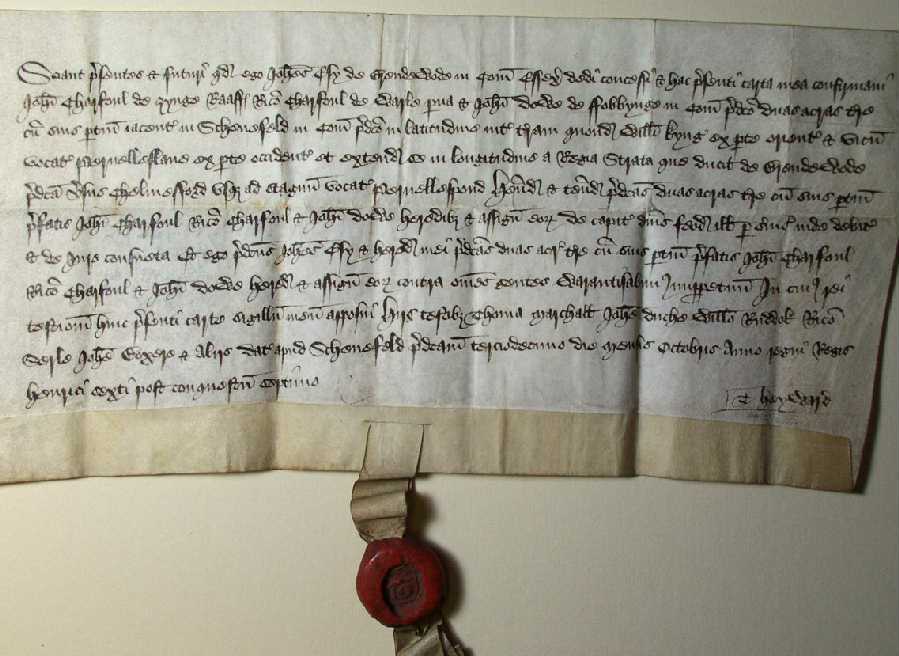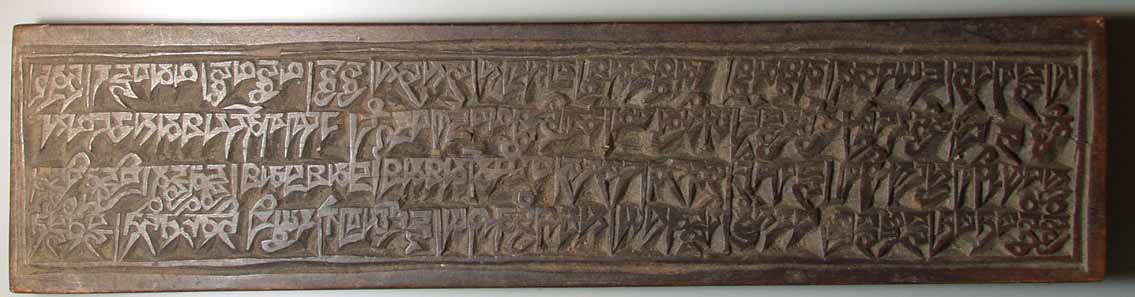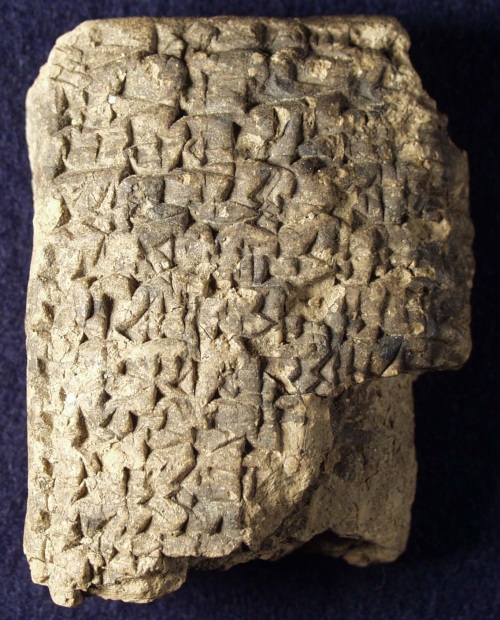
モンゴル時代(13-14世紀)の文字文化(継続)
モンゴル時代(13-14世紀)の文字文化
■各種パスパ文字資料(印鑑、貨幣、銅錘、拓本)
■モンゴル時代諸ハン国貨幣
■その他
世界の“あいうえお表”
〜児童教育用の絵入り大型文字表と文字練習帳〜
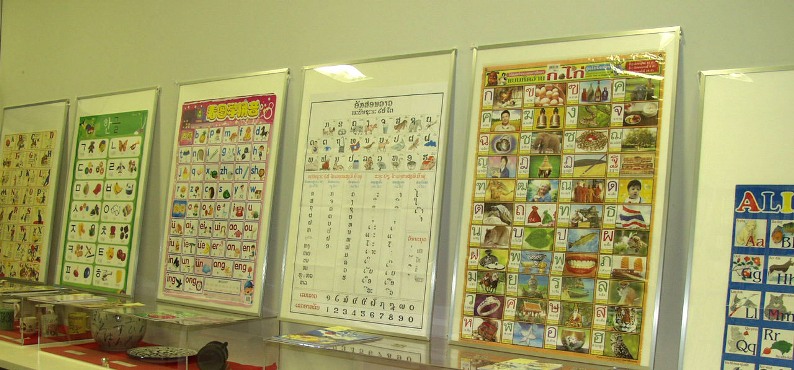
■ 日本 (ひらがな、カタカナ)
■ タイ (タイ文字)
■ 韓国 (ハングル
■ ラオス (ラオ文字)
■ 中国 (漢字、ピンイン)
■ ウズベキスタン (ラテン文字)
■ 中国内蒙古(モンゴル文字)
■ インド (デーバナーガリー文字、オリヤー文字、グルムキー文字、ウルドゥー文字) など
陶磁器と文字 〜古代マヤ文字から、現代ひらがな京都弁まで〜
【土器】
1.彩文土器1(中国。古代。幾何学文様)
2.彩文土器2(中国。古代。象形文様)
【陶磁器】
3.マヤ円筒壺(メキシコ。紀元後600-800年。マヤ文字)
4.日本古地図絵皿(日本。江戸末期。漢字、カタカナの地名)
5.婚姻祝いマグカップ(イギリス。1981年。ラテン文字)
6.マグカップ(イギリス。現代。ロゼッタストーンの文字の写し)
7.マグカップ(韓国。現代。ハングル『訓民正音』の写し)
8.ココ一番屋のマグカップ(日本。現代。四種の文字)
9.湯飲み茶碗(日本。現代。“壽”字の諸体)
10.湯飲み(日本。現代。漢字魚名)
11.湯飲み(日本。現代。ひらがな京都弁と共通語の対訳)
12.カップ(日本。現代。ひらがな長崎弁と共通語の対訳)
13.花器(日本。現代。いろは歌)
14.絵皿(チュニジア。現代。アラビア文字)
【その他陶製品】
15.陶製枕(中国。近代。漢字漢文の対聯)
16.陶製ウシャブティ(エジプト。古代。ヒエログリフ)
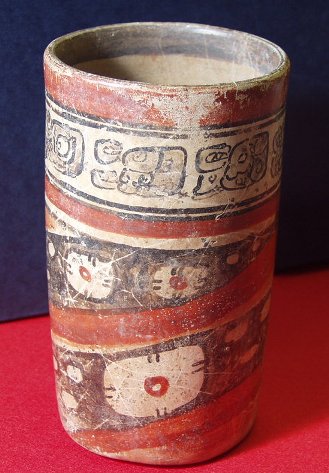
マヤ円筒壺
シルクロードの文字
〜西安からウズベキスタンを経てインド西北に到る〜
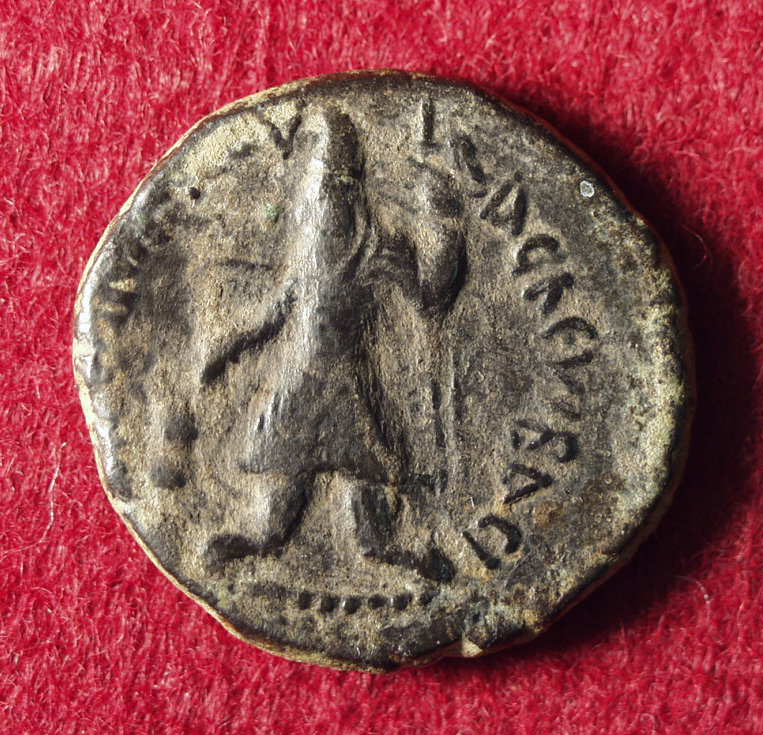
クシャン朝カニシカ王の銅貨(ギリシア文字ギリシア語)
展示資料一覧
1.前漢の五銖銭 紀元前118年〜
2.ソグド人墓の墓誌拓本 紀元580年
3.西夏銭・貞観元寶 紀元1101年〜1113年
4.西夏・銭型の札 紀元1036年〜1227年
5.西夏文布本 紀元1036年〜1227年
6.西域の漢字木簡 時代不明
7.ウイグル文字の銅貨 紀元9世紀〜13世紀
8.亀茲五銖銭 紀元5世紀〜7世紀
9.新彊馬銭 紀元2世紀後半
10ソグド銭・ブハラ開元通寶 紀元7世紀〜8世紀
11.ソグド銭・シシュピール王銅貨 紀元7世紀中期
12.ソグド銭・タルナビッチ王銅貨 紀元7世紀〜8世紀
13.ソグド銭・王肖像銅貨 紀元7世紀〜8世紀
14.バクトリア銭・ミリンダ王銀貨 紀元前2世紀
15.クシャン朝銭・クジュラ・カドフィセス王銅貨 紀元1世紀後半
16.クシャン朝銭・カニシカ王銅貨1 紀元2世紀中頃
17.クシャン朝銭・カニシカ王銅貨2 紀元2世紀中頃
18.シュロ樹葉断片の仏教文書 紀元2世紀〜3世紀
19.アラム文字の獣皮文書 時代不明
20.パピスル断片のギリシア文書 紀元2世紀〜6世紀
21.アレクサンドロス大王の銀貨 紀元前4世紀
22.フィリッポスU世の銀貨 紀元前4世紀
番外:5つの古代文明の文字
23.マヤ文字意匠の円筒形壺 紀元後600年〜800年頃
24.甲骨文字の亀甲断片 紀元前1300年〜前1100年頃
25.インダス文字印章 紀元前2600年〜前1800年頃
26.楔形文字方形粘土板 紀元前2100年〜前2000年頃
27エジプト象形文字パピルス断片 紀元前1200年以降
シルクロードの文字 〜ソグド文字とその末裔〜
写真(左)はソグド貨幣の人物、(右)はソグド文字と紋章(中央)
五つの古代文明の文字〜楔形文字・ヒエログリフ等・漢字・インダス文字・マヤ文字〜
モンゴル時代の文字
中国の民族古文字
古代シルクロードの文字(継続)
古代シルクロードの文字
※展示物40余点は以下のとおりです。
アラム文字資料2点
ブラーフミー文字資料2点
カローシュティー文字資料13点
ソグド文字資料6点
ウイグル文字資料2点
契丹文字資料2点
西夏文字資料6点
パスパ文字資料11点
複数文字資料2点
アルファベットの世界
ラテン文字・ヴェラム
展示内容
セムのアルファベットから、東はカローシュティー文字やソグド文字、西はギリシア文字を
経てコプト文字やラテン文字(ローマ字)が生まれます。今回の展示では、アルファベット
の歴史を概観するとともに、中世ヨーロッパ文書の美しさを堪能して頂きたいと
思っております。
総計20点余
〈
アラム文字〉獣皮、〈
カローシュティー文字〉貨幣、〈
ソグド文字〉貨幣。
〈
ギリシア文字〉銀貨。パピルス断片。〈
コプト文字〉パピルス断片。
〈
ラテン文字1〉共和政ローマ銀貨。帝政ローマ銀貨、銅貨。
〈
ラテン文字2〉教父時代文書(ヴェラム断片2行、ドイツ10世紀)。シトー修道会写本(ヴェラム
断片4行、フランス12世紀中頃)。小型聖書(ヴェラム一葉、イタリア13世紀中頃)。聖書(ヴェラム
一葉、フランス13世紀中頃)。詩篇集(ヴェラム一葉、イギリス14世紀)。時祷書(ヴェラム一葉、
フランス15世紀中頃)。時祷書(ヴェラム一葉、フランス15世紀末〜16世紀初)。
法廷文書(ヴェラム完全、イギリス1429年)。特許状(ヴェラム完全、イギリス1573年)。イギリス銀貨。
メソポタミア・エジプト・ギリシアの文字
〈メソポタミア〉
1.円形小型粘土板(シュメールの楔形文字)紀元前2700-2500年。大麦の領収書。受取人の名も刻まれている。
2.粘土釘(新シュメールの楔形文字)。紀元前2192-2111年。太い円錐の粘土に奉献文が刻まれている。
3.方形小型粘土板(新シュメールの楔形文字)。紀元前2112-2004年。大麦の領収書。円筒印章が押されている。
4.円筒印章(1)(新シュメールの楔形文字)。紀元前2192-2004年の前期。大麦の祭壇の両側に人物が配される図。所有者を示す楔形文字が二行。
5.円筒印章(2)(バビロニアの楔形文字)。紀元前2004-1596年の後期。戦棍を持つ王が嘆願の女神と向き合う図。所有者を示す楔形文字が三行。
6.粘土板封筒(バビロニアの楔形文字)。紀元前2004-1596年。封筒とおもわれる。中の文書は確認できない。側面に二カ所、円筒印章が押されている。
7.大型粘土板の角部分小断片(バビロニアの楔形文字)。紀元前2004-1596年。
〈エジプト〉
8.パピルス断片(エジプト神聖文字)。紀元前1200-200年。『死者の書』。
9.亜麻布断片(エジプト神官文字)。紀元前400-200年。『死者の書』文言ふくむ。
10.パピルス断片(エジプト民衆文字)。紀元前700-200年。商業関係文書。
11.石板断片(エジプト神聖文字)。紀元前1400年頃。アメンヘテプ3世の王名あり。
12.ウシャブテイ(エジプト神聖文字)。時代不明。ファイアンス制。男性人名あり。
13.パピルス断片(a)(コプト文字)。紀元後400-700年。商業文書。
14.パピルス断片(b)(コプト文字)。紀元後400-700年。法律文書。
〈ギリシャ〉
15.テトラドラクマ銀貨(ギリシャ文字)。紀元前148年以降。ディオニュソス神とヘラクレス
16.パピルス断片(筆記体ギリシャ文字)。紀元後200-600年。商業文書。